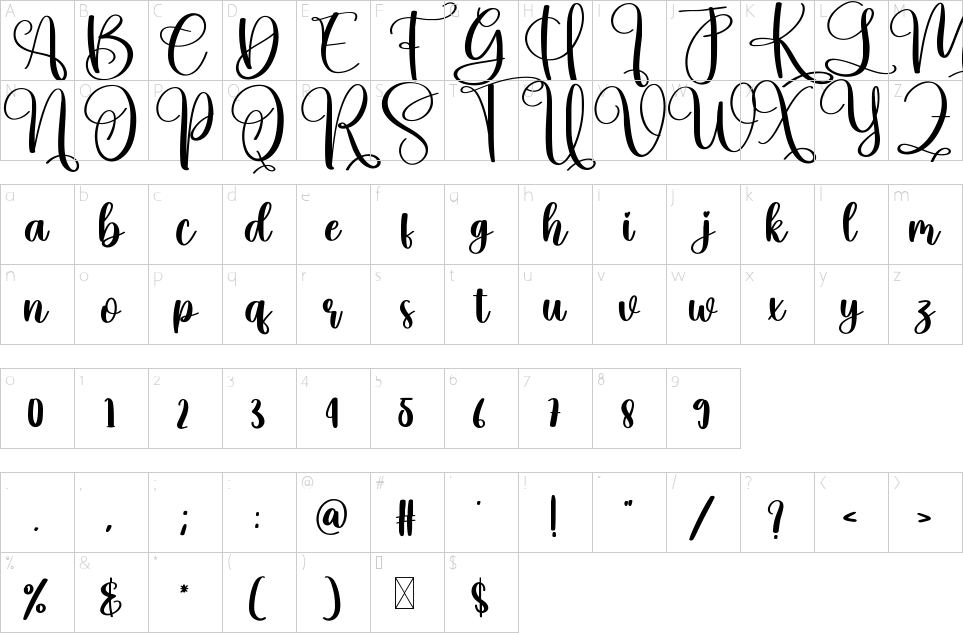
A Dance Font é uma seleção única para quem procura uma fonte que transmite movimento e energia através dos caracteres escritos. Desenvolvida por scratchones, a Dance Font foi projetada para aqueles que buscam um estilo versátil que se adapta perfeitamente tanto ao mundo da moda digital quanto à criação de materiais educacionais ou até mesmo álbuns pessoais. Com uma estrutura elegante e cores vibrantes, essa fonte é ideal para quem procura uma maneira criativa de personalizar seu material gráfico em versões Windows e Mac. Oferecida gratuitamente, ela já foi baixada por 818 usuários, evidenciando o seu potencial para tornar qualquer layout mais atraente e dinâmico. Se você está procurando uma opção elegante e vibrante para seus projetos, Dance Font é um excelente ponto de partida para explorar.